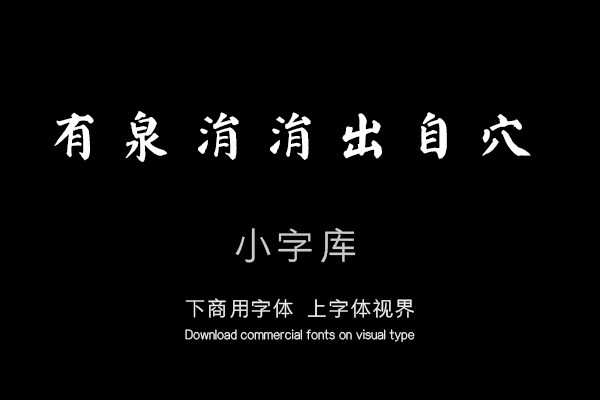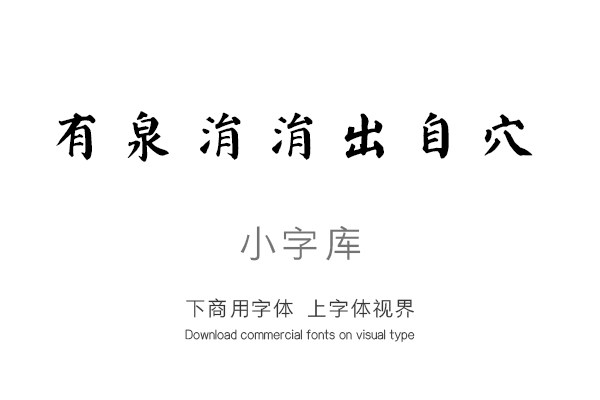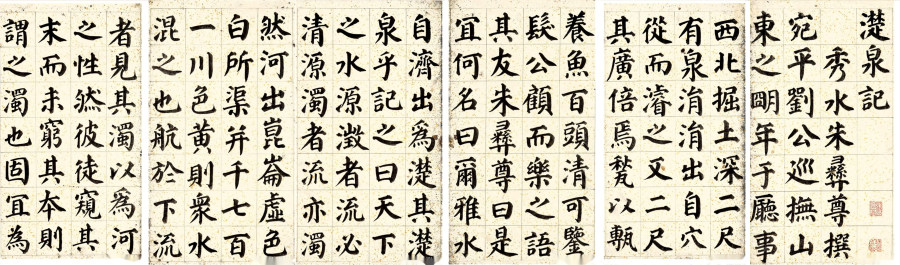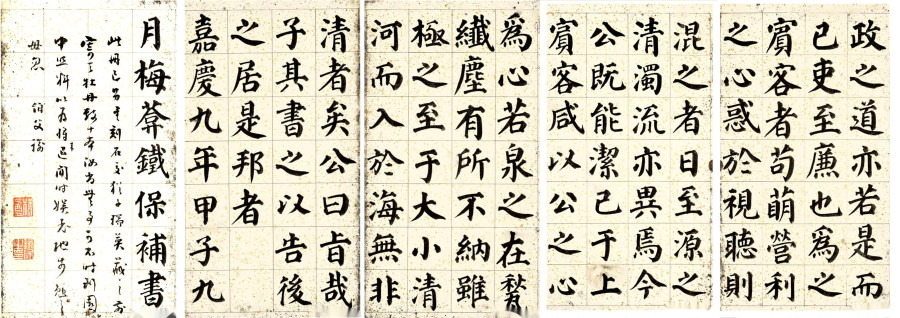
汉标铁保楷书濋泉记
《汉标铁保楷书濋泉记》是一款根据清代铁保楷书《濋泉记》,经过再次调整制作的小字库,该小字库共收录了该真迹作品中约335个字体。
濋泉记。秀水朱彝尊撰。宛平刘公巡抚山东,之明年于厅事西北掘土,深二尺,有泉涓涓出自穴,从而浚之,又二尺,其广倍焉,甃以砖养鱼百头,清可鉴髪,公顾而乐之语,其友朱彝尊曰:“是宜何名日尔雅,水自济出为濋,其‘濋泉’乎?” 记之曰:“天下之水,源澄者,流必清;源浊者,流亦浊。然河出昆仑虚,色白;所渠并千七百一川,色黄,则众水混之也。航於下流者,见其浊,以为河之性。然彼徒窥其末而未穷其本,则谓之浊也固宜。为政之道亦若是而已。吏至廉也,为之宾客者苟萌营利之心,惑於视听,则混之者日至。源之清浊,流亦异焉。今公既能洁已于上,宾客咸以公之心为心,若泉之在甃,纤尘有所不纳,虽极之至于大小清河,而入於海,无非清者矣。公曰旨哉子其书之以告后之居是邦者。嘉庆九年甲子九月,梅葊铁保补书。